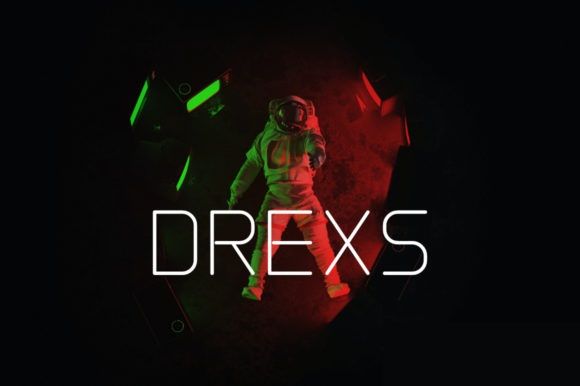
Название: DREXS Font
Drexs - это простой, тонкий и футуристический шрифт.
Независимо от того, используете ли вы его для оформления веб- или научно-фантастических проектов, этот шрифт легко выделится из толпы.
Отлично подходит для брендинга, словесного знака, логотипа, дизайна логотипа, заголовка, дизайна пользовательского интерфейса и т.д.
Название: DREXS Font
Drexs - это простой, тонкий и футуристический шрифт.
Независимо от того, используете ли вы его для оформления веб- или научно-фантастических проектов, этот шрифт легко выделится из толпы.
Отлично подходит для брендинга, словесного знака, логотипа, дизайна логотипа, заголовка, дизайна пользовательского интерфейса и т.д.